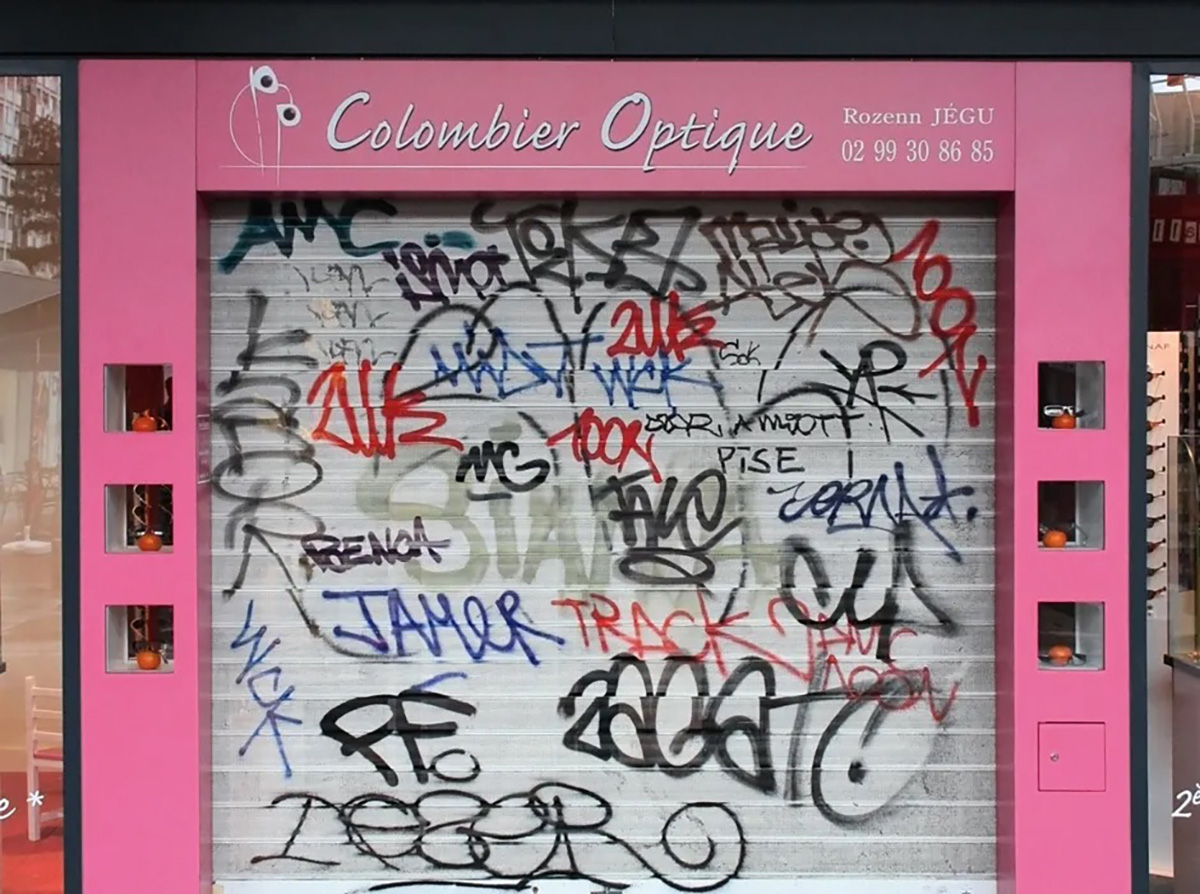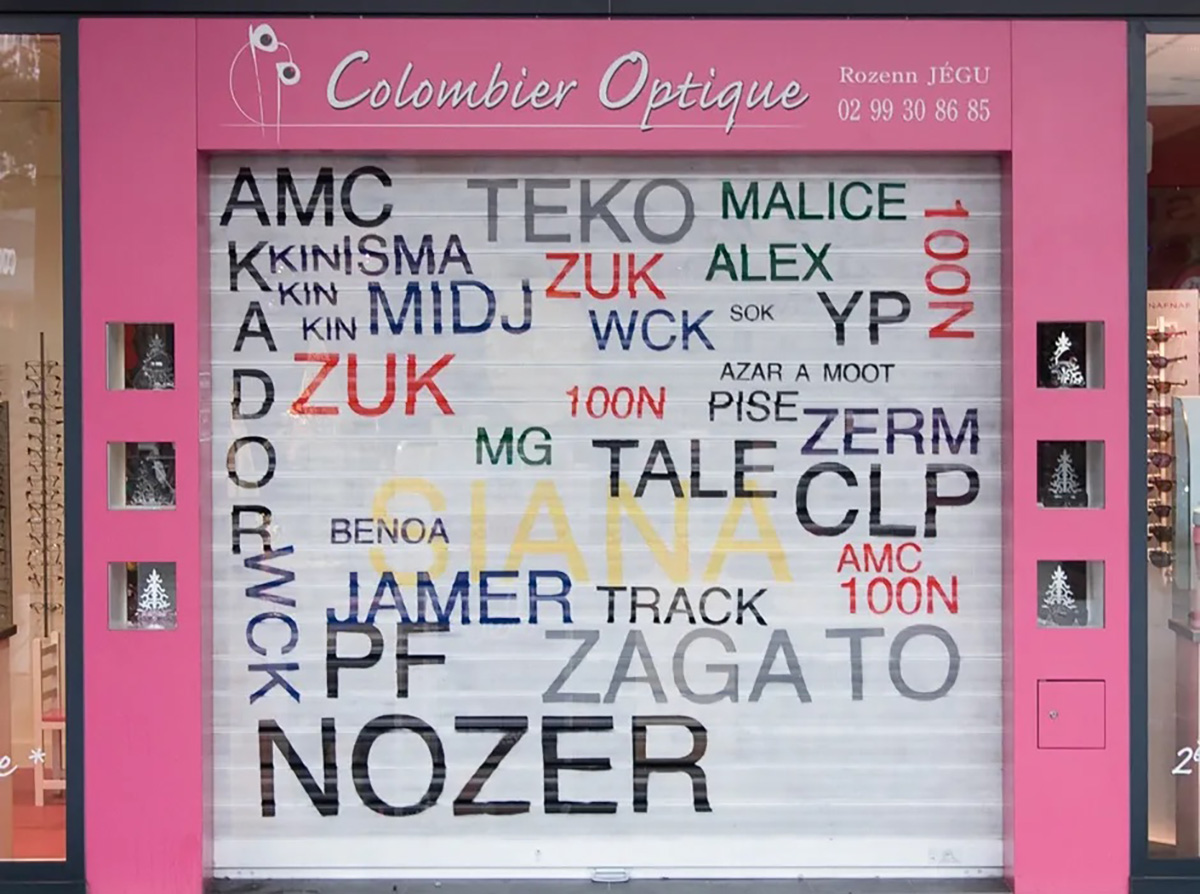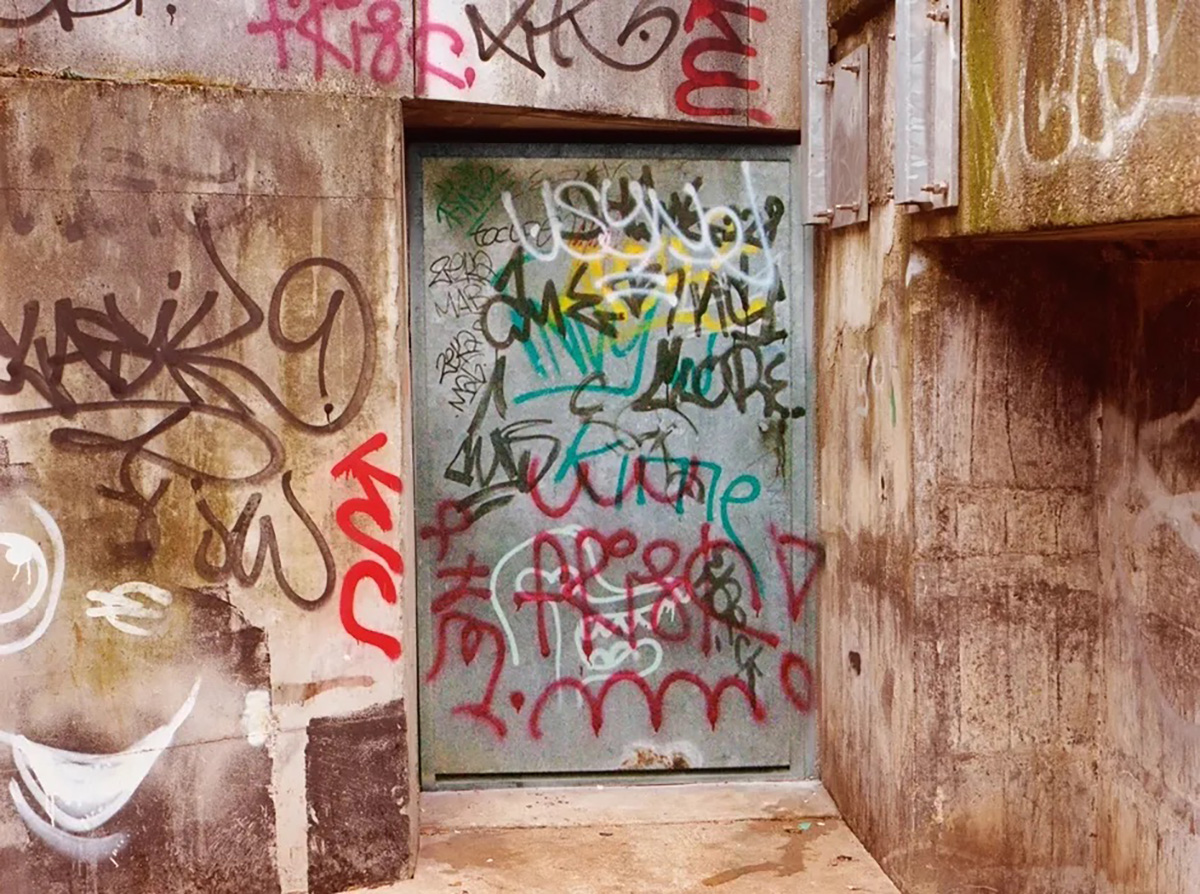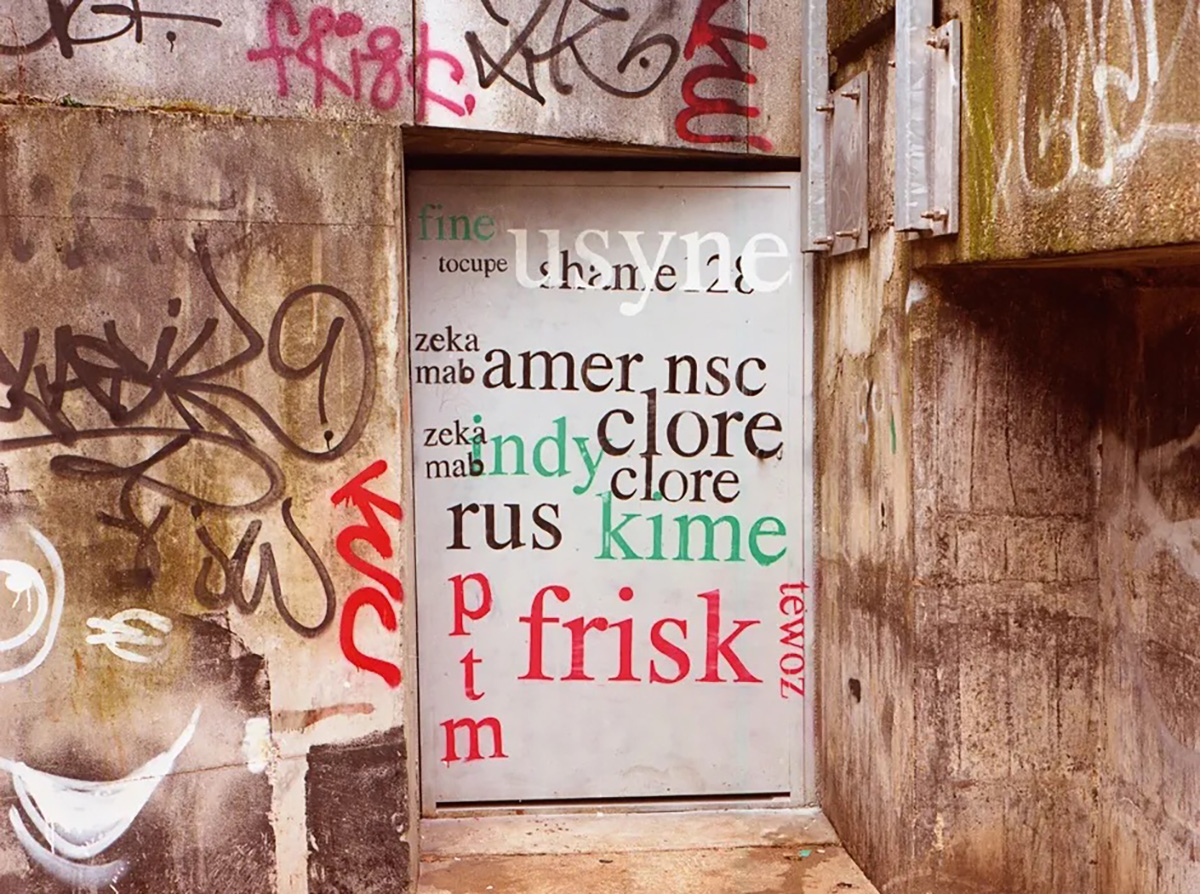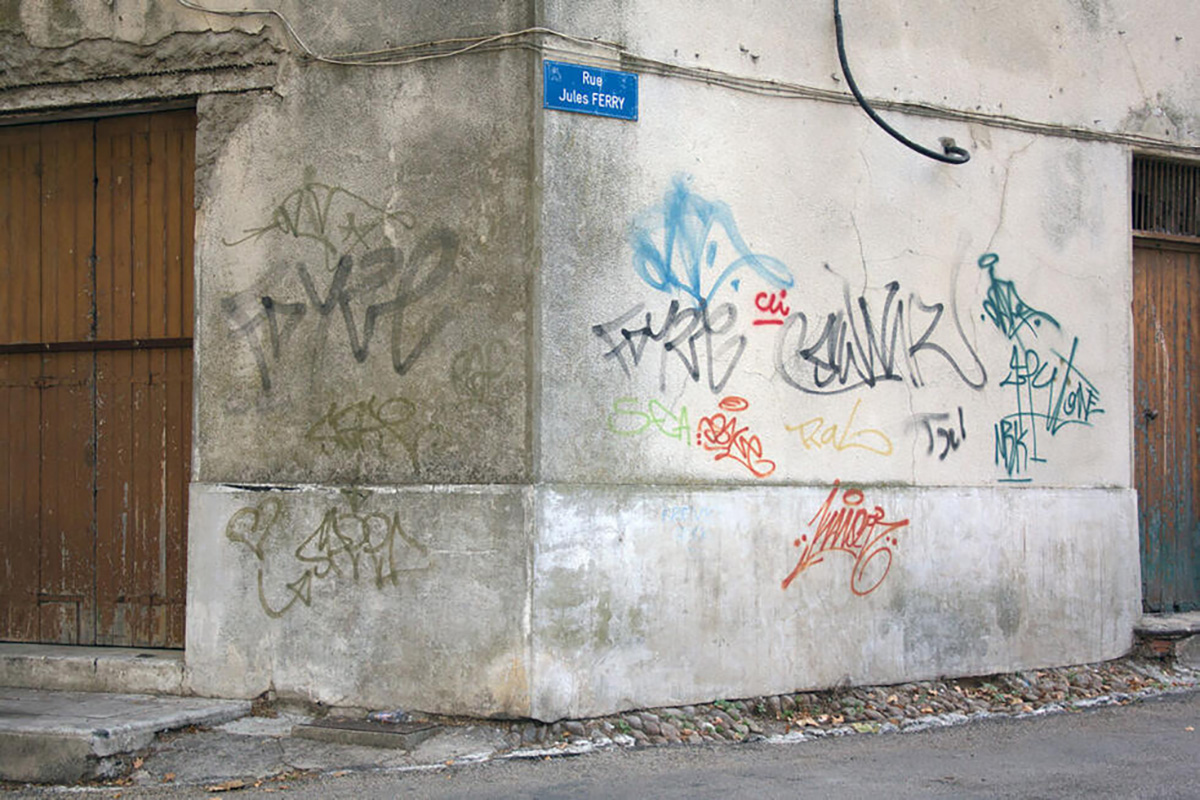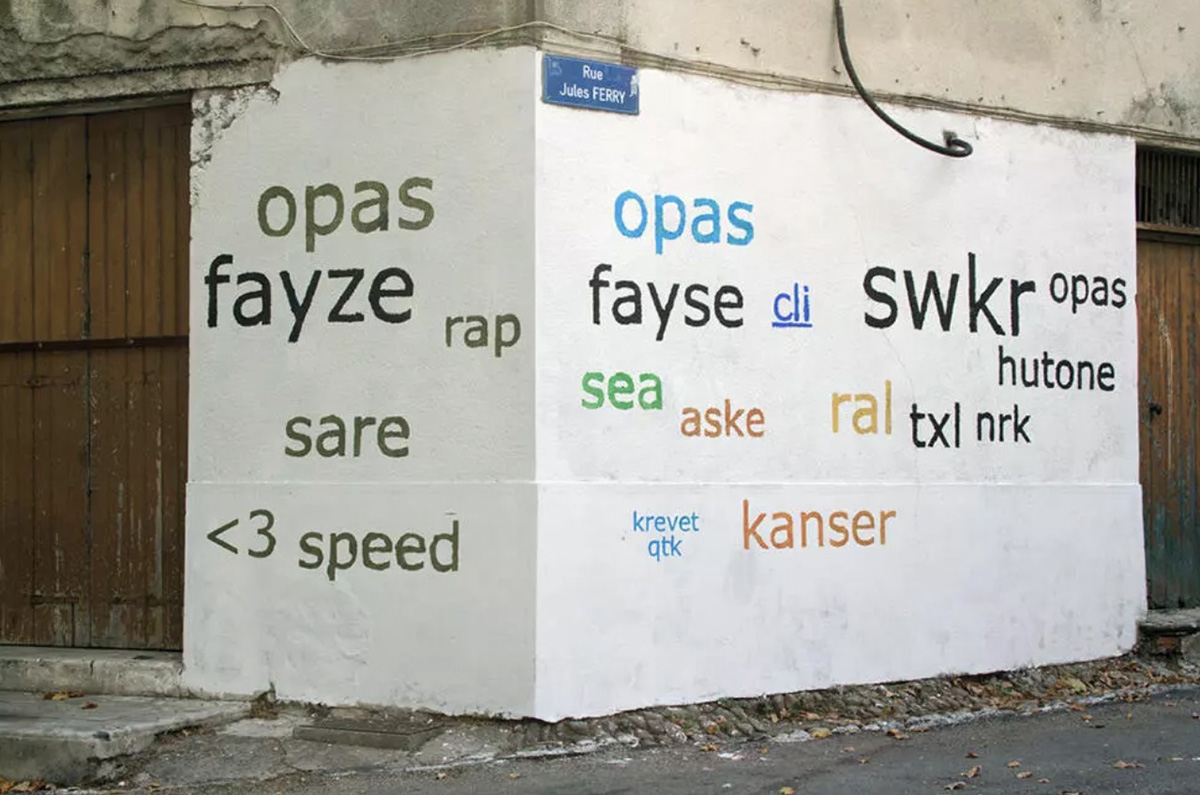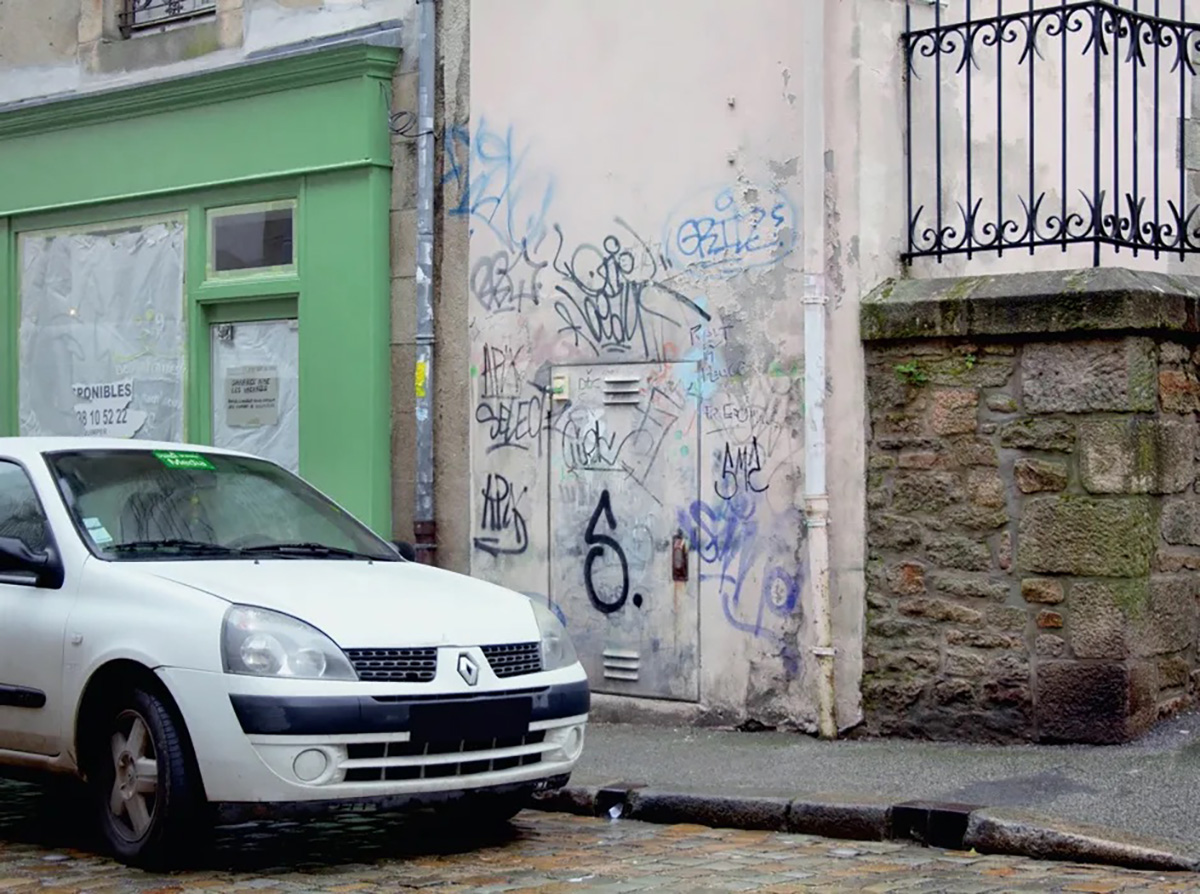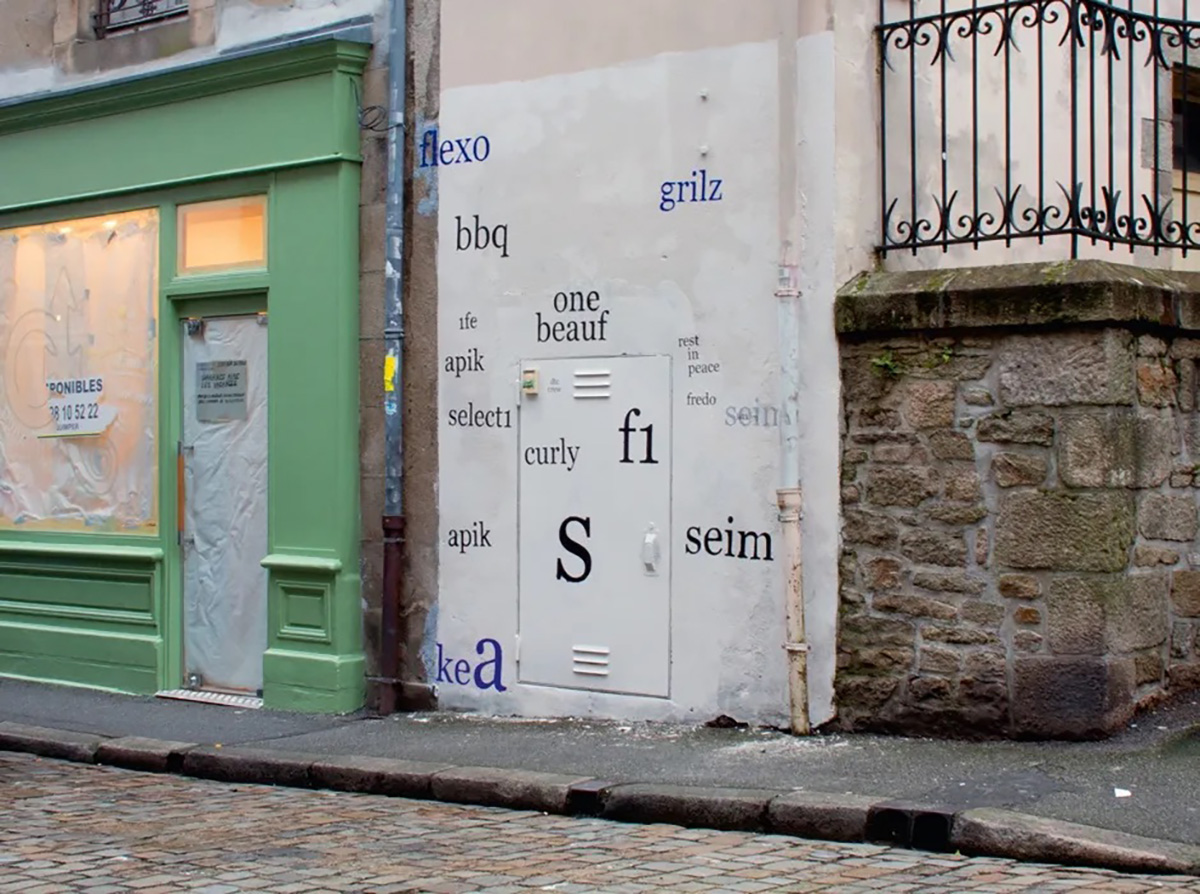
Dans les rues, les tags sont partout. Pourtant, rares sont ceux qui prennent le temps de les lire, ou simplement de les comprendre. Face à cette écriture codée que seuls les initiés peuvent déchiffrer, l’artiste français Mathieu Tremblin (@tremblinsays) propose une approche radicalement différente : réécrire les graffitis en typographie lisible, sans en trahir le message d’origine. Une démarche à la fois artistique et provocante qui questionne notre rapport à l’espace urbain.
Ce projet, baptisé “Tag Clouds”, a récemment refait surface sur les réseaux sociaux par le collectif WAVE, qui documente quotidiennement ce que fait la culture sous l’angle du sport, de la musique, de la mode ou encore de l’art. En mettant en lumière cette initiative singulière, le collectif met en valeur une réflexion plus large sur les langages visuels urbains et leur pouvoir de narration.
Un alphabet caché dans la ville
Dans le cadre de son projet, l’artiste parcourt les murs pour recouvrir les signatures des graffeurs, en les reproduisant sous une typographie standardisée. Le geste n’est pas anodin : il permet aux passants de lire ce qui, d’ordinaire, reste crypté. Comme des mots-clés dans une “cloud tag” numérique, ces graffitis prennent ici une forme plus lisible… tout en conservant leur mystère.
Mais cette intervention suscite aussi le débat, notamment dans la communauté du graffiti où recouvrir une œuvre (même pour la “traduire”) est perçu comme une transgression. Une tension assumée par l’artiste, qui revendique l’importance de cette friction pour questionner les règles implicites de l’espace public.
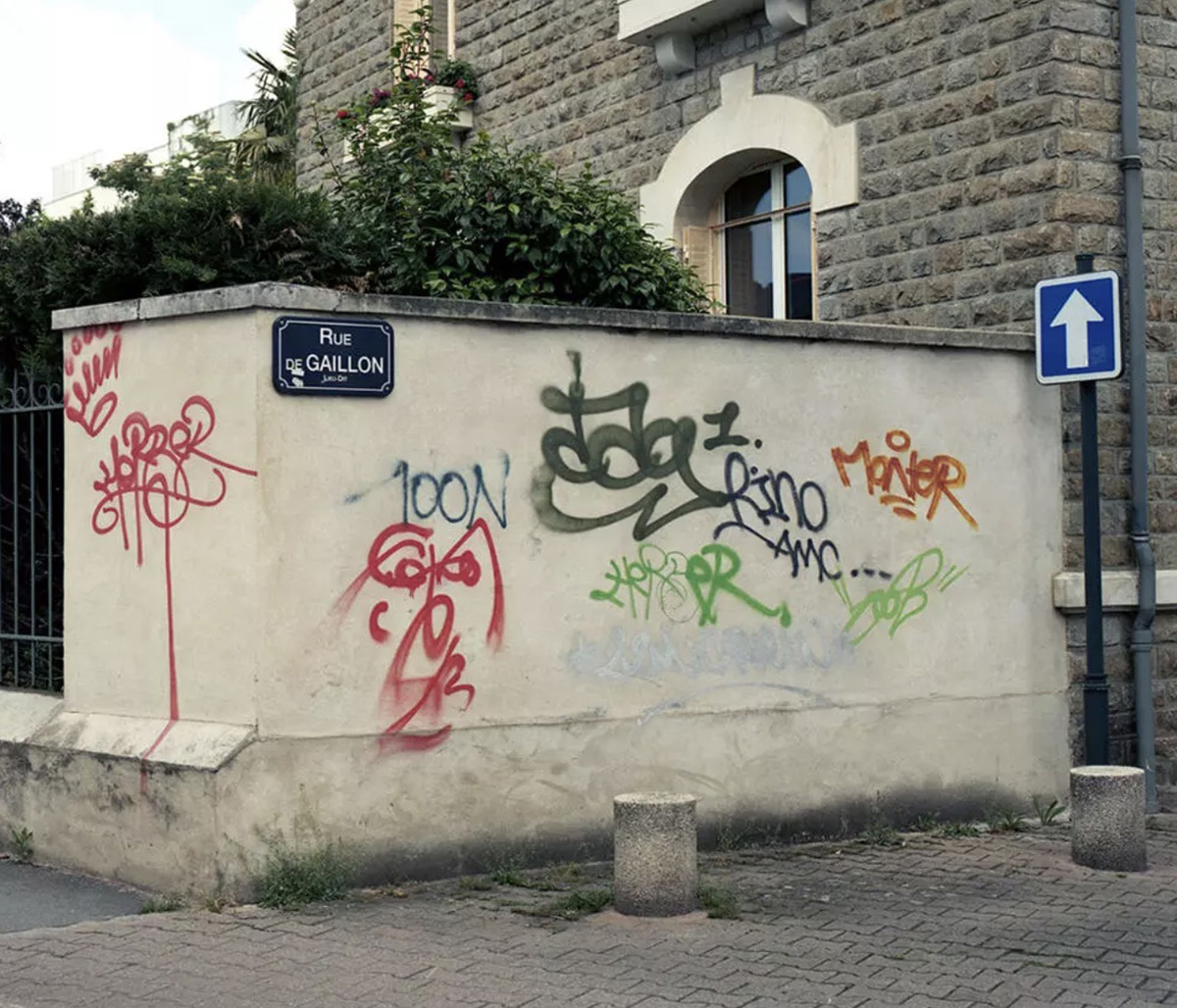
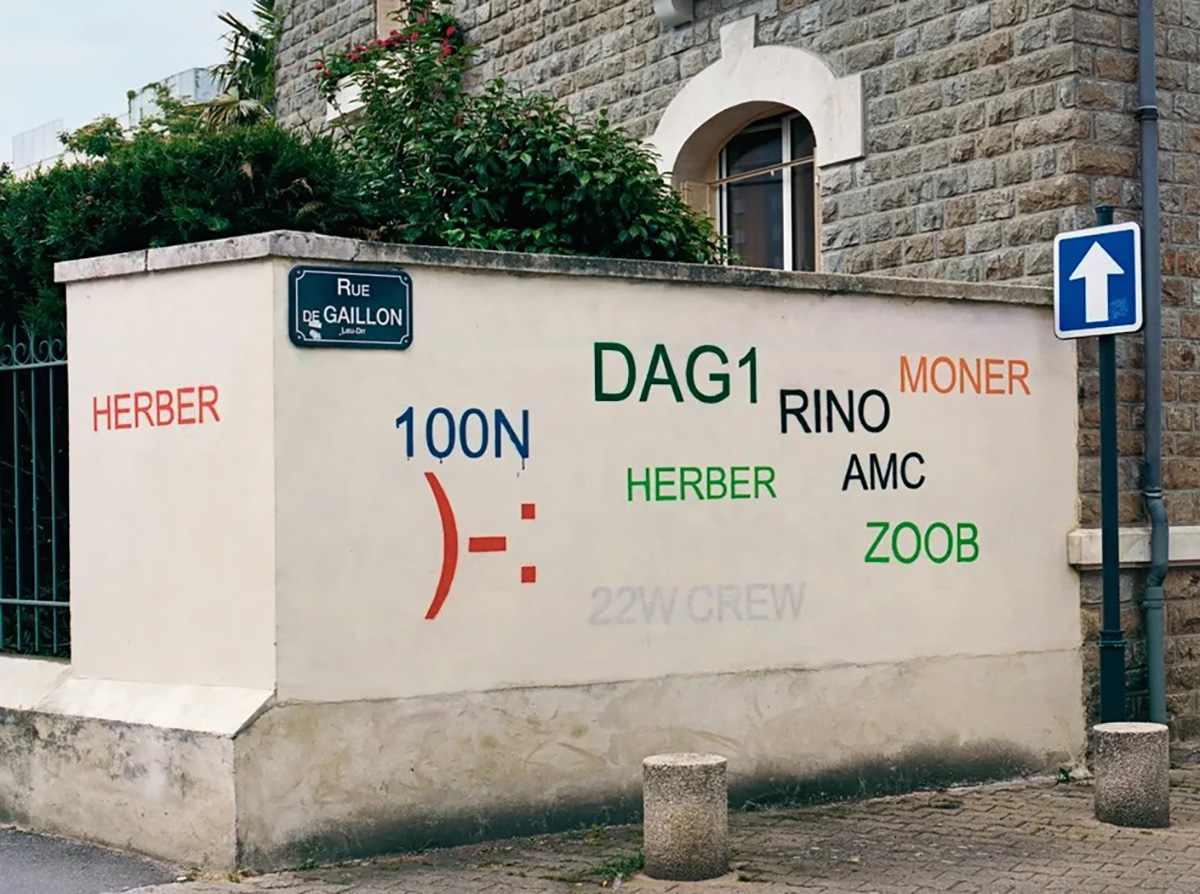
Une critique de la ville “optimisée”
Plus qu’un exercice de typographie, le projet interroge la manière dont la ville est gérée, organisée, parfois aseptisée. Pour Mathieu Tremblin, s’intéresser aux tags, c’est refuser de suivre les trajets balisés imposés par les flux économiques, politiques ou touristiques. C’est réintroduire de l’aléatoire, du personnel, de l’émotion dans une cartographie trop fonctionnelle.
Et surtout, c’est rappeler que la ville appartient aussi à ceux qui la marquent, qui y laissent une trace. Ou, pour reprendre les mots de l’artiste : “Ce ne sont pas les tagueurs qui s’approprient la ville… ce sont les tags qui lui appartiennent.”
Au-delà du street-art
Si ses performances évoquent immédiatement le street-art, le graffeur rejette cette étiquette, trop marketing à ses yeux. Selon lui, le terme a été instrumentalisé par le marché de l’art, reléguant les graffitis “sauvages” au rang de sous-culture. Lui préfère parler d’intervention urbaine critique, consciente de son environnement et affranchie des codes commerciaux.